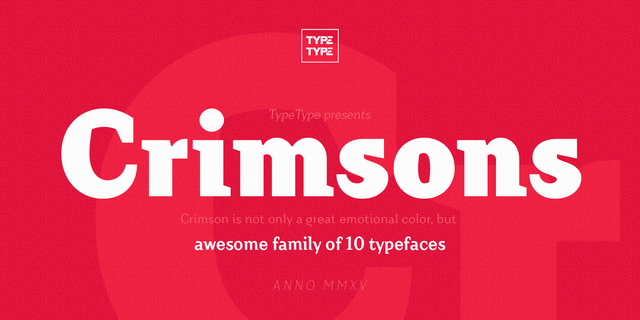
Шрифт Crimsons уникален и очень необычен. Он совмещает форму новых гротесков и пропорции старостильных антикв. Это шрифтовое семейство очень пригодится для коллекции дизайнера. Crimsons идеален для коротких и эмоциональных надписей. Тутулы, имена, логотипы – это его стихия. Шрифт содержит самый популярный набор начертаний: Тонкое, Светлое, Нормальное, Жирное, Сверхжирное и наклонные начертания к ним. Crimsons разработан в студии TypeType в 2015 году.
твердый, оригинальный, характерный, острый, ломаный, резкий, четкий, серьезный, городской, необычный, странный, гордый, устойчивый, современный, динамичный, артистичный, дорогой, техничный, чеканный, хрупкий, прозрачный, ровный, экспериментальный, стеклянный, проволочный, худой, железный, стальной, жесткий, суровый, уверенный, надежный, урбанистический, авторитетный, убедительный, важный, монументальный, архитектурный, экстравагантный, амбициозный, тяжелый, сильный, броский, заметный, яркий, активный